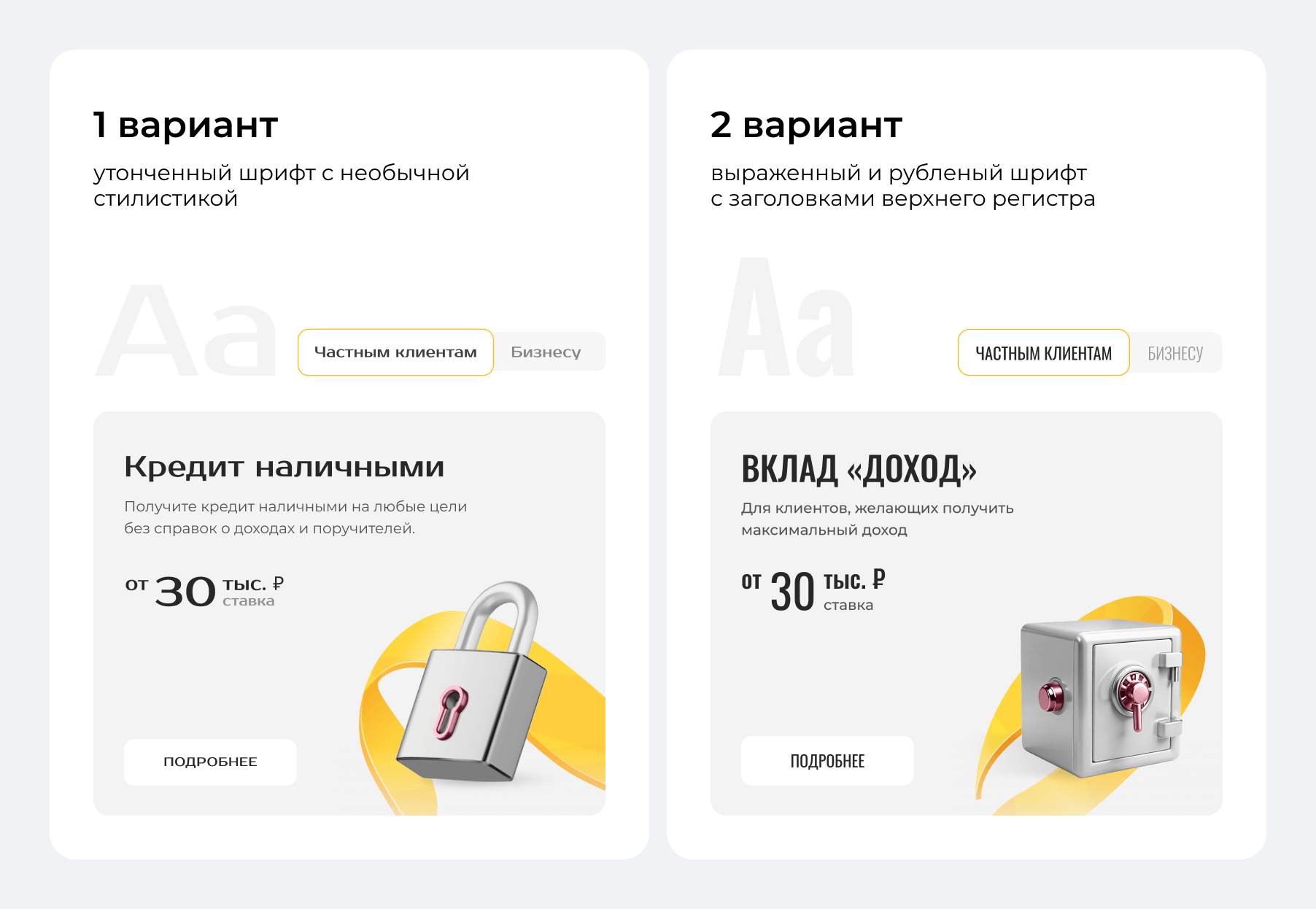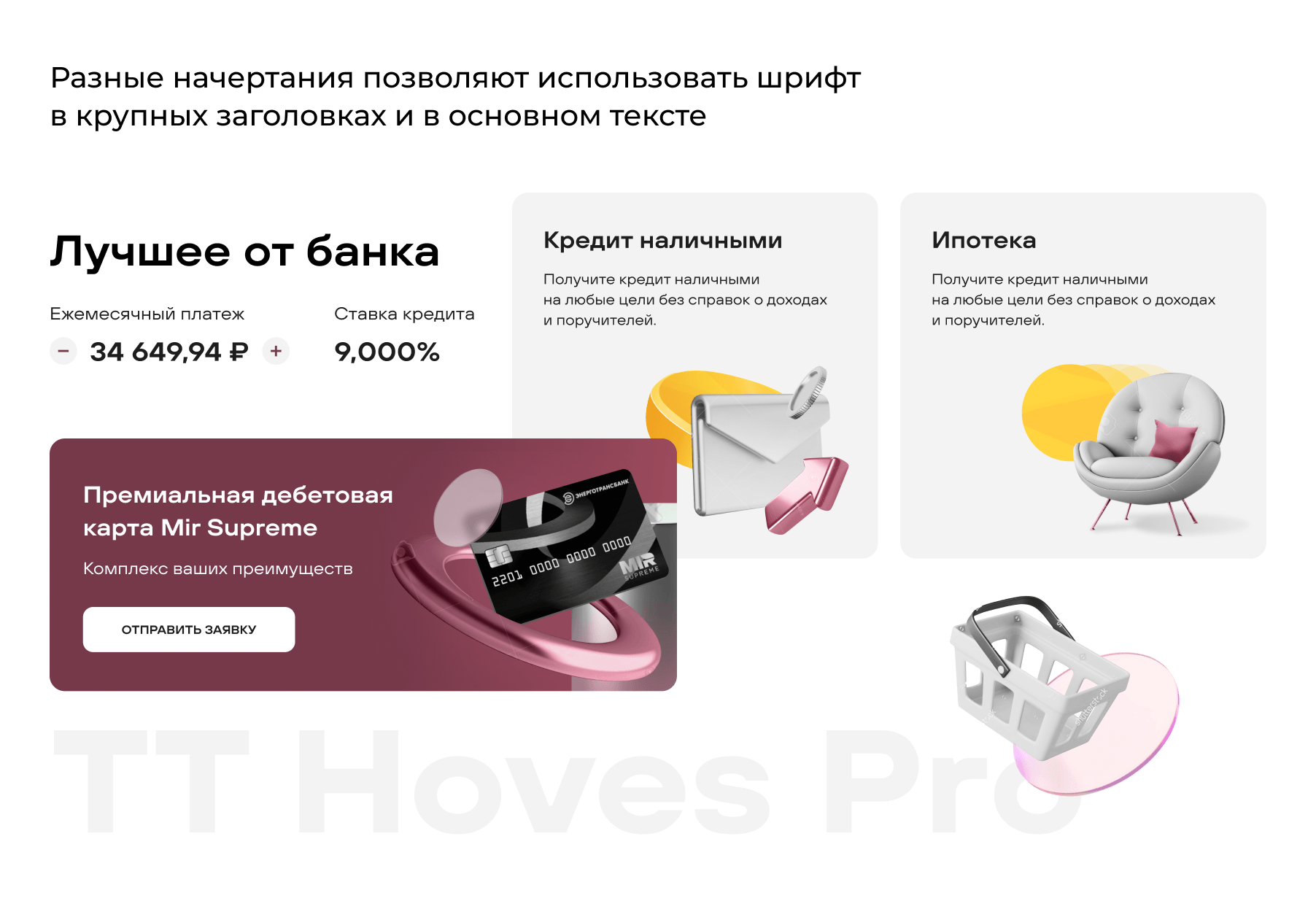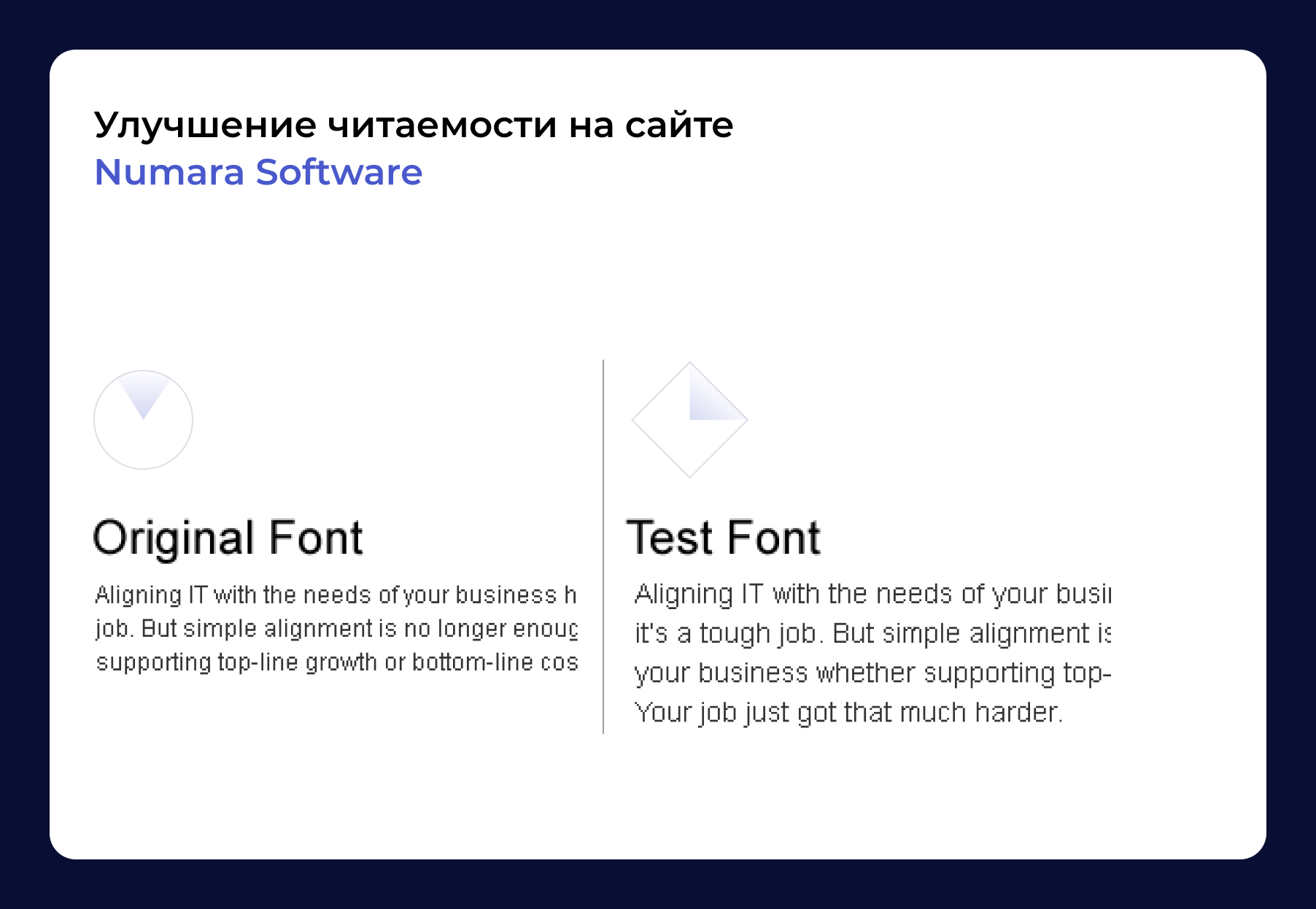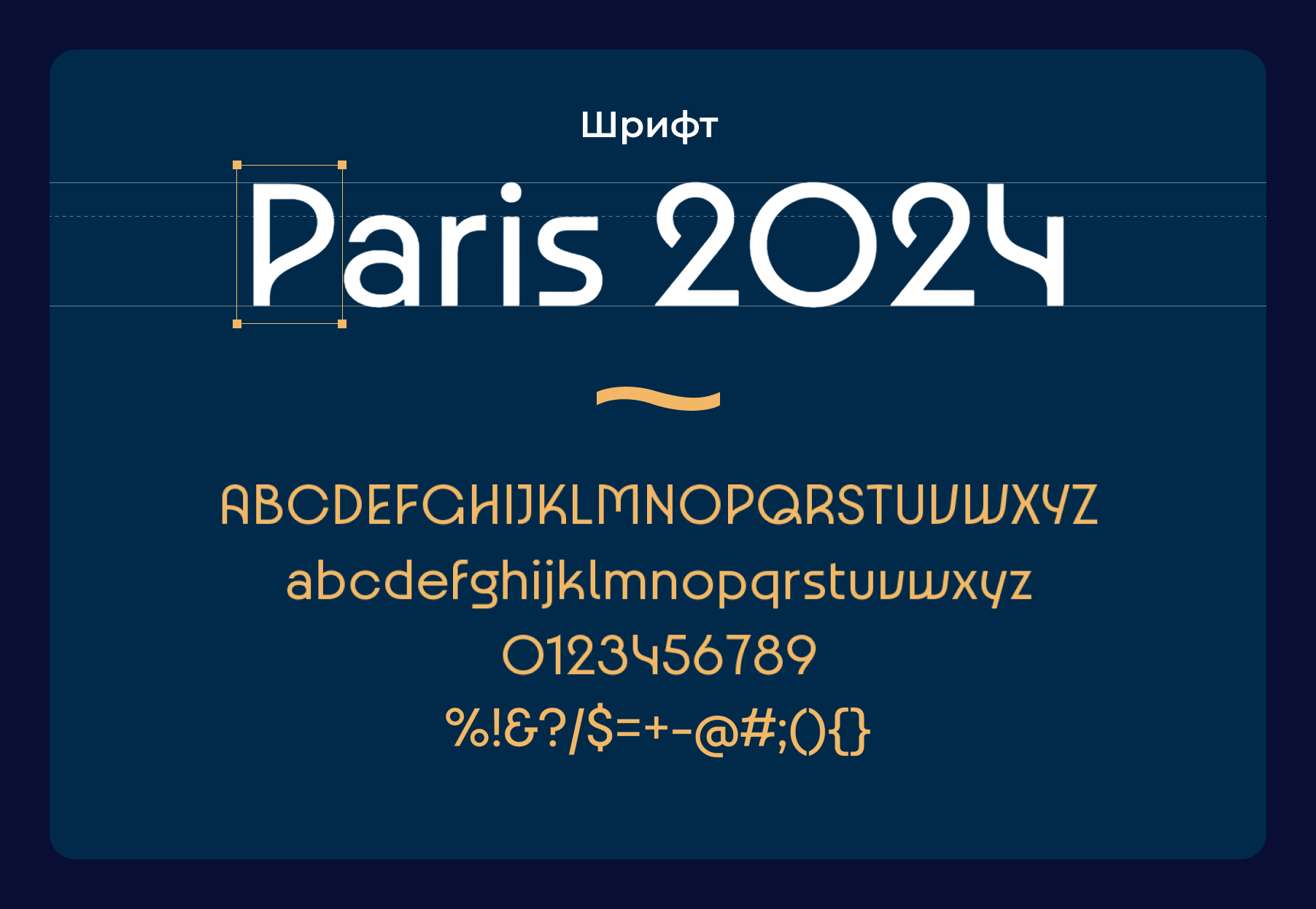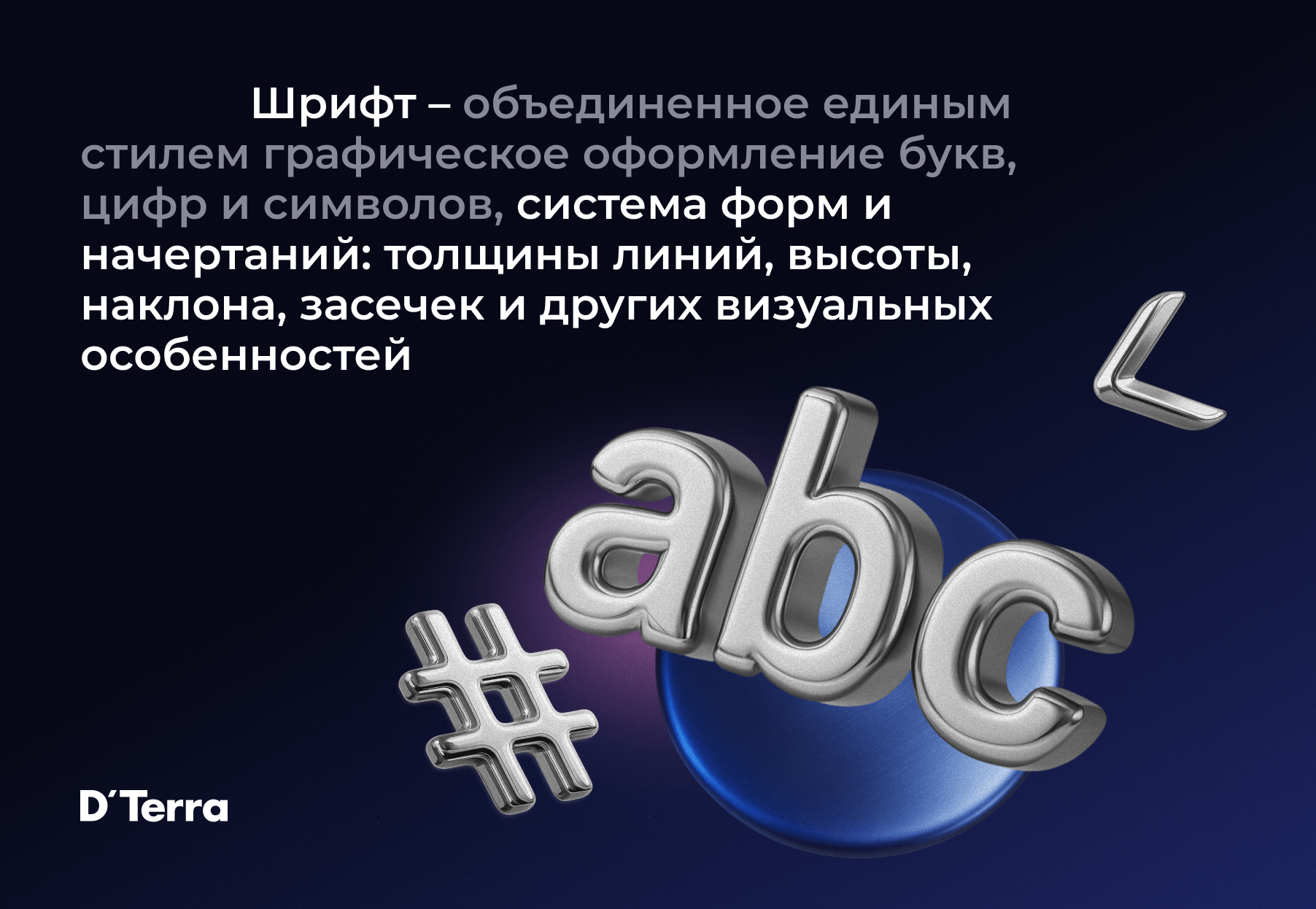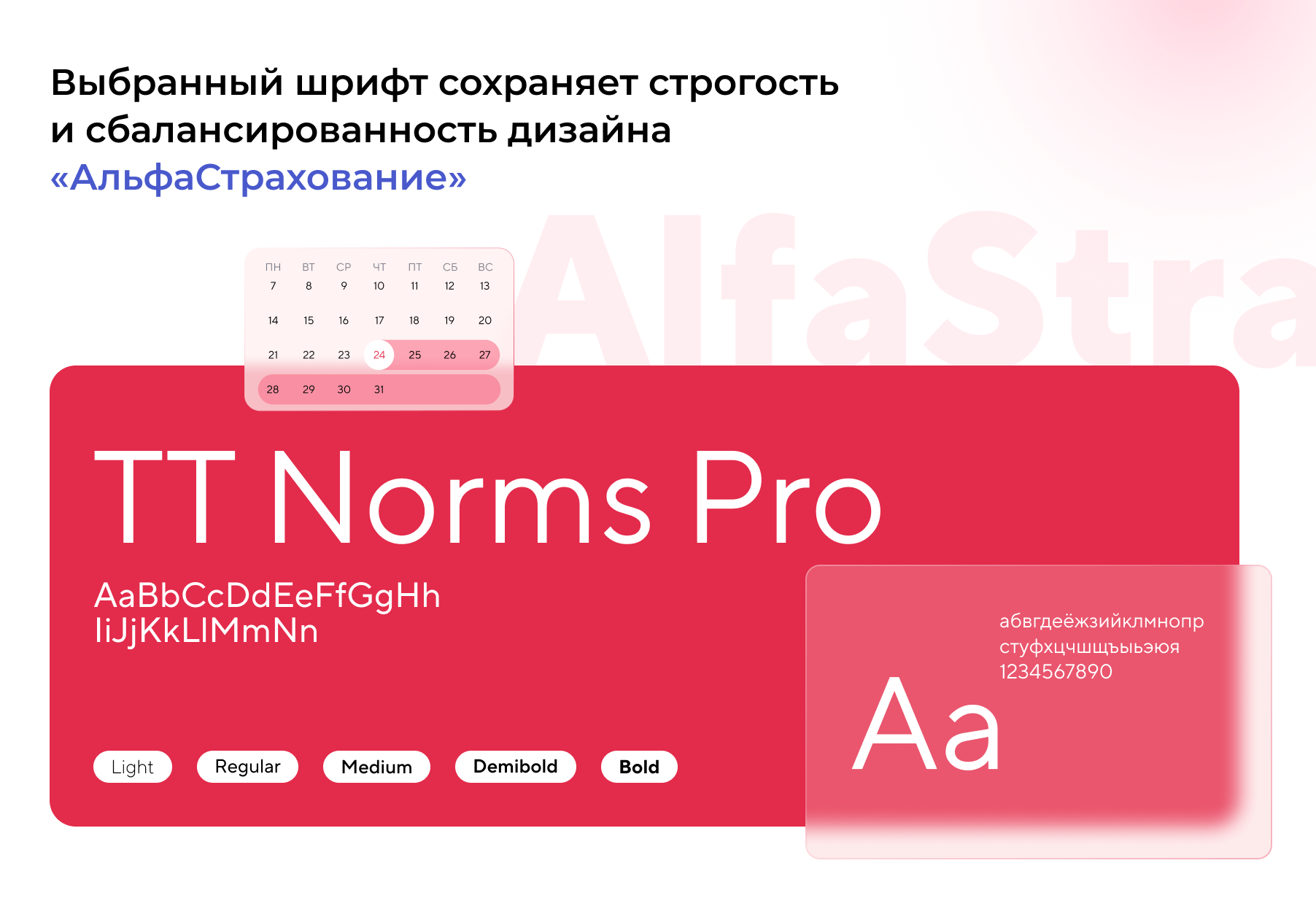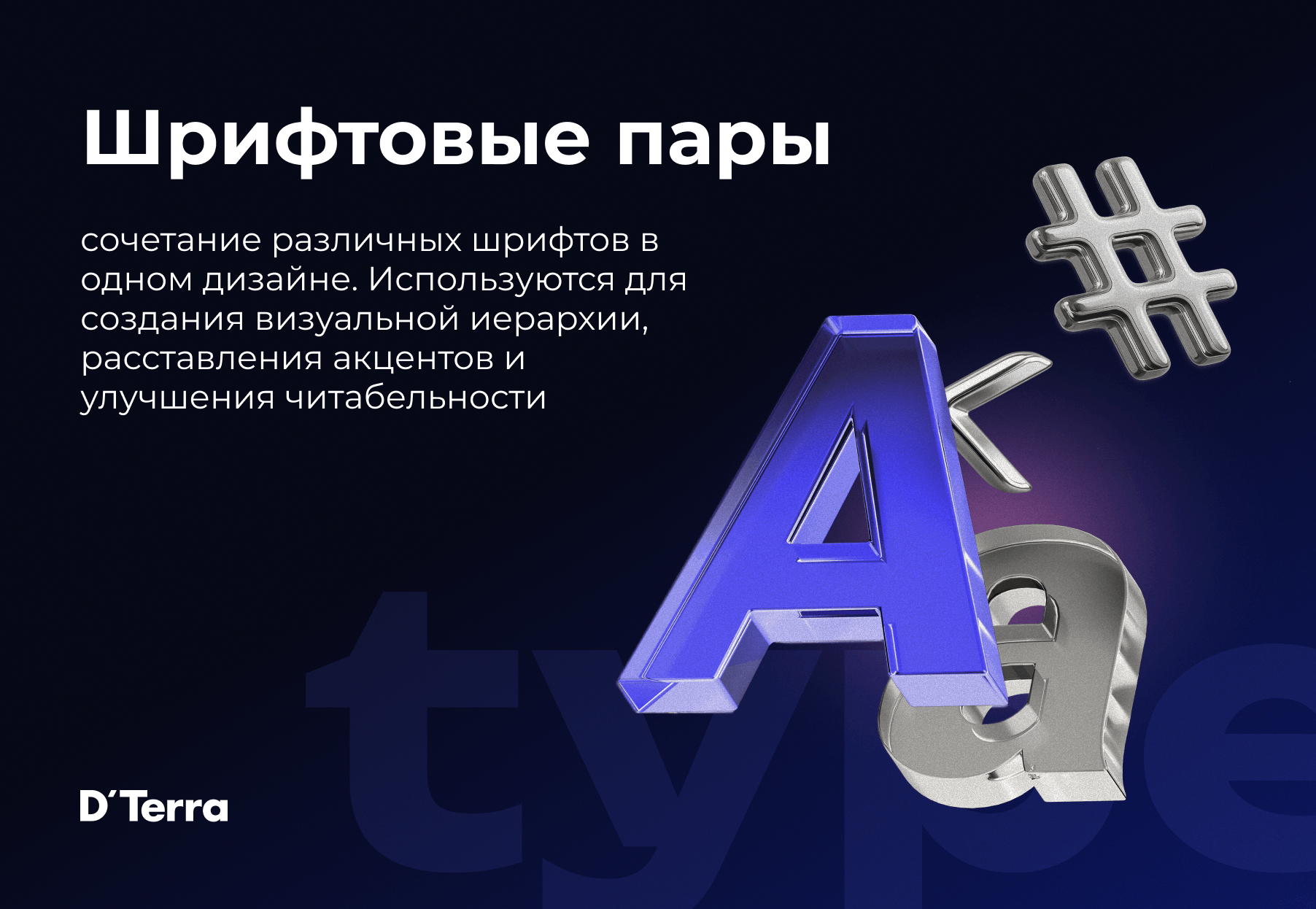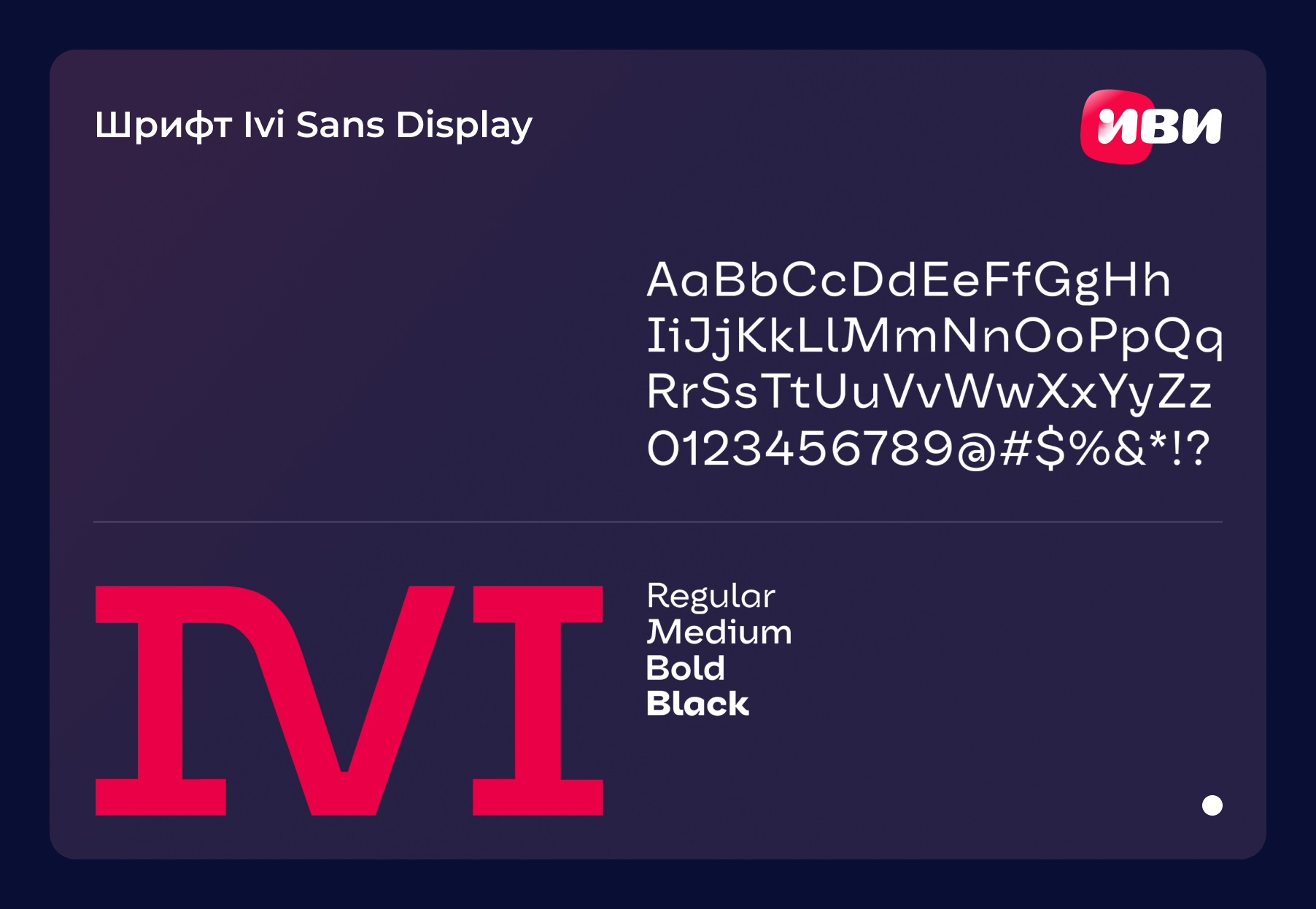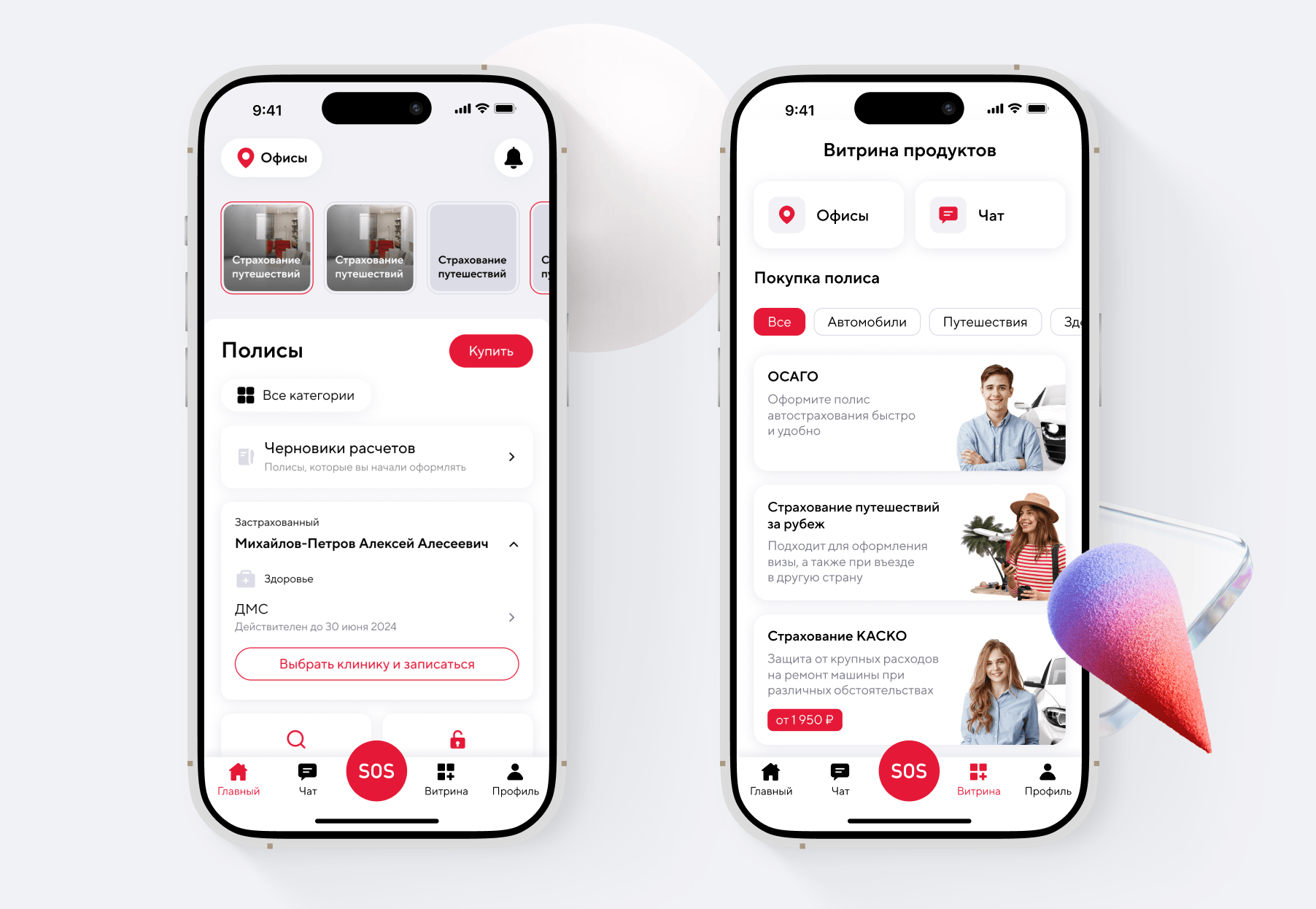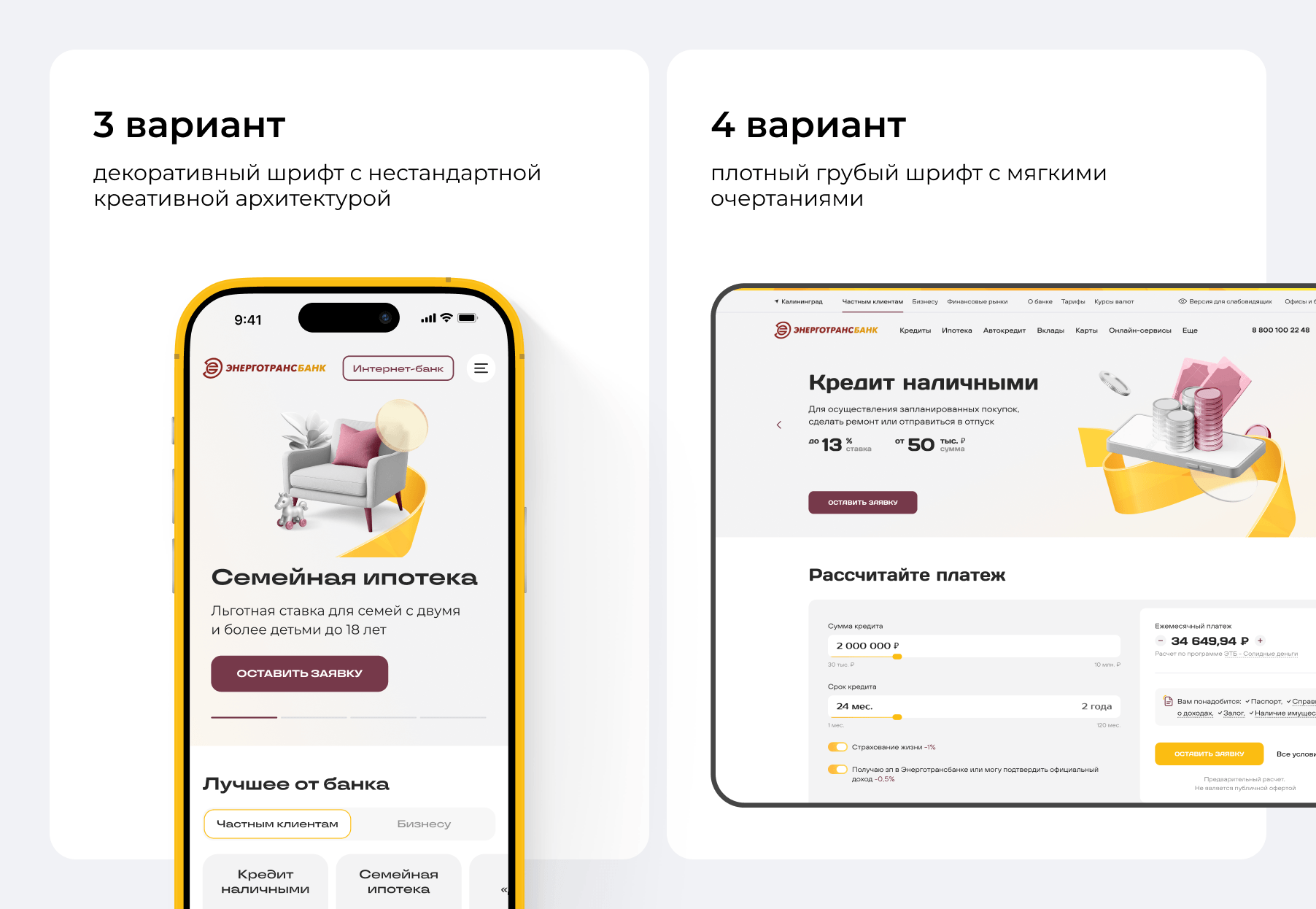
Для чего покупать шрифты, если доступны бесплатные? В статье разберем преимущества уникальных шрифтов и процесс подбора.
Веб-пользователи видят десятки шрифтов в интерфейсах сайтов и приложений. Шрифт стал инструментом коммуникации и полноценной частью брендинга как логотип и цвет. Он формирует впечатление, влияет на читаемость и даже на доверие к контенту. Согласно исследованию AgeLab MIT мнение о бренде формируется на основе типографики.
Мировой рынок веб-шрифтов в 2023 оценивался в 2.9 миллиарда $, к 2031 прогнозируется рост на 9.5%, по данным компании в сфере исследований Verified Market Reports. Интерес бизнеса к уникальным шрифтам растет из-за тренда на персонализацию и потребности в гибкой настройке.
Кастомный шрифт помогает четко доносить информацию за счет визуальной точности и технической проработки. Он акцентирует внимание на содержании, упрощает восприятие текста и ускоряет считывание смысла. В работе с массивами данных и цифрами шрифт остается функциональным и при этом через фирменный стиль создает ассоциацию с брендом, – руководитель проектного офиса TypeType Сергей Кузьмин
Масштаб компании не влияет на то, подходящим ли будет бесплатное решение. Небольшой бизнес также конкурирует визуально. Бесплатные шрифты свободно используются во всех сферах. Они не отражают индивидуальность и размывают бренд на фоне компаний с одинаковой типографикой.
Собственный шрифт нужен не всем. Если в интерфейсе мало текста, сайт играет роль временной заглушки или проект ограничен бюджетом, то на старте вполне подойдут готовые шрифты. Оценивайте этап развития компании и типографические потребности, – Art Director D'Terra Анастасия Колышкина
Шрифт визуально выделяет бренд. Наглядный пример – VK. Компания использует собственную гарнитуру как элемент экосистемы бренда.
Кастомный шрифт отражает характер бренда. К примеру, шрифт Paris 2024 для Олимпийских игр подчеркивает визуальную идентичность события и отсылает к ар-деко – стилю последних Игр в Париже в 1924.
С ростом бренды переходят к коммерческим проработанным шрифтам с более выразительной айдентикой. К примеру, после ребрендинга онлайн-кинотеатр «Иви» сменил шрифт на более дружелюбный.
Бесплатные шрифты не имеют тех. поддержки, возможности для развития и кастомизации. Готовые шрифты перегружены лишними символами и стилями, они не используются, но загружаются в браузер – увеличивается вес страницы. Кастомный шрифт технически оптимизирован под проект – меньше вес, выше скорость загрузки.
Адаптивный дизайн усиливает спрос на шрифты, которые удобно читать на любых устройствах без нагрузки на зрение. Пример: после изменения межстрочного интервала компания Numara Software улучшила коэффициент конверсии форм на 133%.
Использование платного шрифта исключает юридические риски и ограничения по лицензии. Шрифт полностью принадлежит компании: доступно использование в любых каналах и форматах.
TypeType – крупнейшая студия шрифтового дизайна, которая 12 лет разрабатывает гарнитуры и кастомные шрифты. Среди клиентов – Uniqlo, Vogue, VK, «Точка Банк». В команде работают 80+ специалистов из разных стран. Кроме того, TypeType – партнер конференции «Дизайн-выходные», фестиваля «Среда», конкурса ADCR.
Кастомный шрифт – важная часть брендинга. В дизайн-лаборатории D'Terra мы создаем визуальные решения, где типографика – ключевой элемент коммуникации. Анализируем задачи, разрабатываем концепцию и вместе с TypeType реализуем шрифтовую часть. Внедряем инструмент, который улучшает пользовательский опыт и решает маркетинговые задачи, – Art Director D'Terra Анастасия Колышкина
Команда D'Terra за 4 месяца разработала PWA-приложение для iOS и Android с основным функционалом и привычным интерфейсом. На основе существующей дизайн-системы реализованы обновления разделов. Внедрение нового шрифта – отдельная задача от клиента в рамках проекта.
Процесс подбора шрифта начинается с анализа
1. Определение идентичности бренда и изучение ЦА
2. Оценка существующей айдентики
3. Проверка текущего шрифта на соответствие позиционирования
4. Определение целевых критериев
5. Оценка визуального контекста и анализ трендов
Шрифт интегрирован в дизайн-систему – макеты для десктопа, планшета и мобильных устройств. На их основе будут создаваться страницы сайта.
Кастомный шрифт – инвестиция в узнаваемость и доверие пользователя.